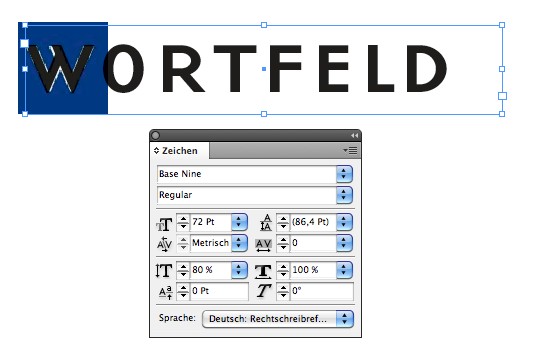
Welche Schrift mag das hier sein?
Kommt mir bekannt vor, aber ich komme nicht drauf.
Größer hab ich es leider auch nicht.
ähnlich wäre auch noch die eagle:
oder die gotham
Beim "W" versteh’ ich nur Bahnhof … aber der Rest passt leider nicht.
Eine in der Höhe gequetschte Base Nine käme auch noch in Frage …
Das mit der in der Höhe gequetschten Base Nine kann ich mir nicht vorstellen. Das Original sieht gar nicht gequetscht aus.
so sähe das aus, ist aber auch nur 95%ig …